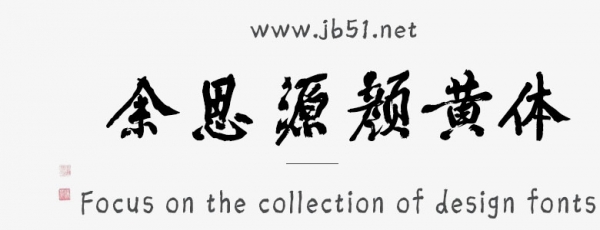
余思源顏黃體是一款不錯的藝術字體,字體線條粗細適中,筆法中變化豐富,方圓結(jié)合保留了許多字體飛白又不像江湖體般張牙舞爪,辨識度較強,具有很好的視覺感,適合應用于藝術設計、平面宣傳設計、網(wǎng)頁設計,書法字帖等領域,需要的朋友可以前來本站下載。
將中唐大書法家顏真卿的書法特點與宋四家之一的黃庭堅的風格結(jié)合。顏真卿筋骨的厚重感與黃庭堅的長槍大戟融為一體,實現(xiàn)渾厚酒脫的行楷風格。用筆上保留個人書寫習慣的同時表現(xiàn)外拓厚重、撇捺舒展、橫畫千里陣云等特點,讓字體有較強的書法氣息又不失設計感。字體強調(diào)書法的傳承也兼具現(xiàn)代設計的需求。
余思源顏黃體相較于如今市面上的行楷書法字體線條粗細適中,筆法中變化豐富,方圓結(jié)合保留了許多字體飛白又不像江湖體般張牙舞爪,辨識度較強,是一款擁有簡體中文繁體中文與英文希臘等符號的一款較為完整的行楷書法字體,適用于多類設計場合。